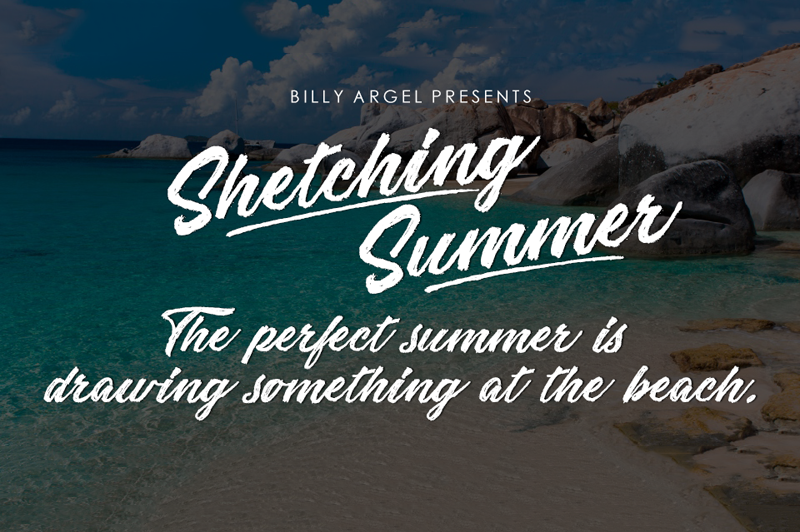
Sketching Summer Font – Download Grátis
A Sketching Summer Font é uma escolha perfeita para quem busca uma fonte script suave e elegante. Desenvolvida pelo designer Billy Argel, a fonte oferece um toque casual e versátil que se adequa perfeitamente para aplicações como cartões de aniversário, designs de lembranças ou até mesmo para adicionar um toque delicado em trabalhos de arte gráfica. Ideal para quem busca uma solução elegante sem perder a personalidade única, Sketching Summer é uma excelente opção tanto para projetos pessoais quanto para usos comerciais moderados. Com seu estilo suave e fluido, esta fonte oferece um leque interessante de opções para criar designs gráficos atemporais e sofisticados. Sua aplicação não está limitada ao papel ou tela digital; a Sketching Summer também se adapta bem para criação de logotipos, editoriais, letras d’água e até mesmo para decorar elementos digitais com um toque delicado e criativo. Com seu uso restrito permitido, esta fonte é perfeita para designers independentes que buscam uma maneira de incorporar um elemento único e personalizado em seus trabalhos sem encarecer sua carreira profissional. A versão completa está disponível no site da Billy Argel (www.billyargel.com), onde você também encontrará muitos outros recursos interessantes relacionados ao design gráfico. Seja para decorar suas criações de arte ou criar um estilo único em seus projetos, a Sketching Summer Font é uma escolha sólida e profissional que reflete o trabalho detalhado e criativo dos designers modernos. Visite agora www.billyargel.com para saber mais sobre todas as outras fontes disponíveis do designer!